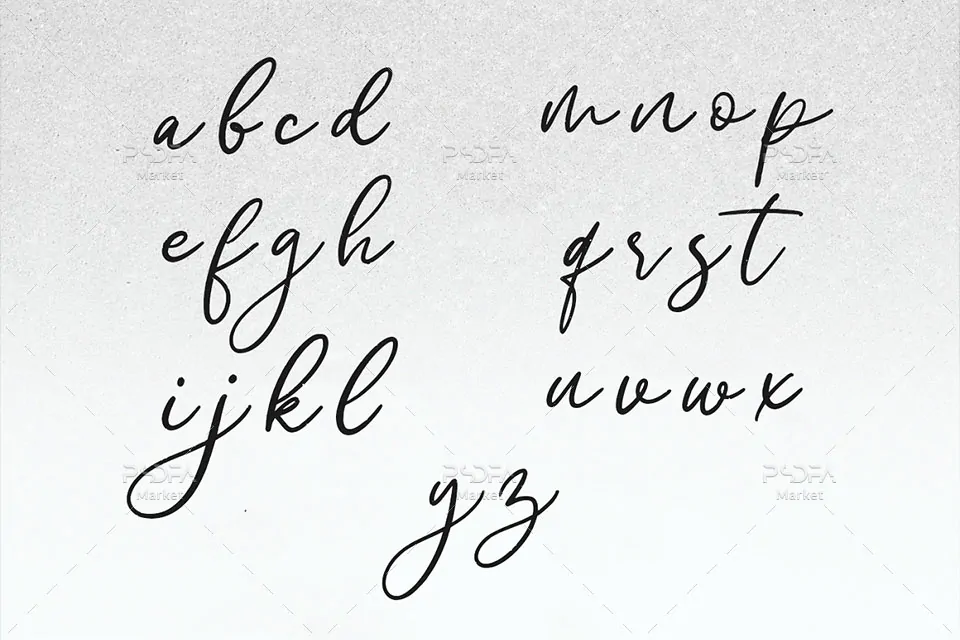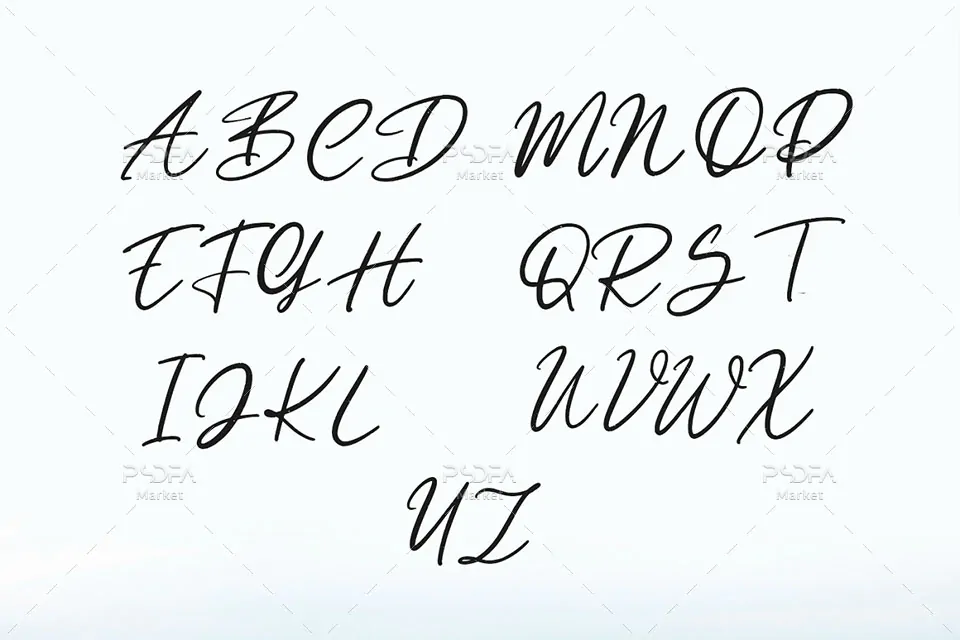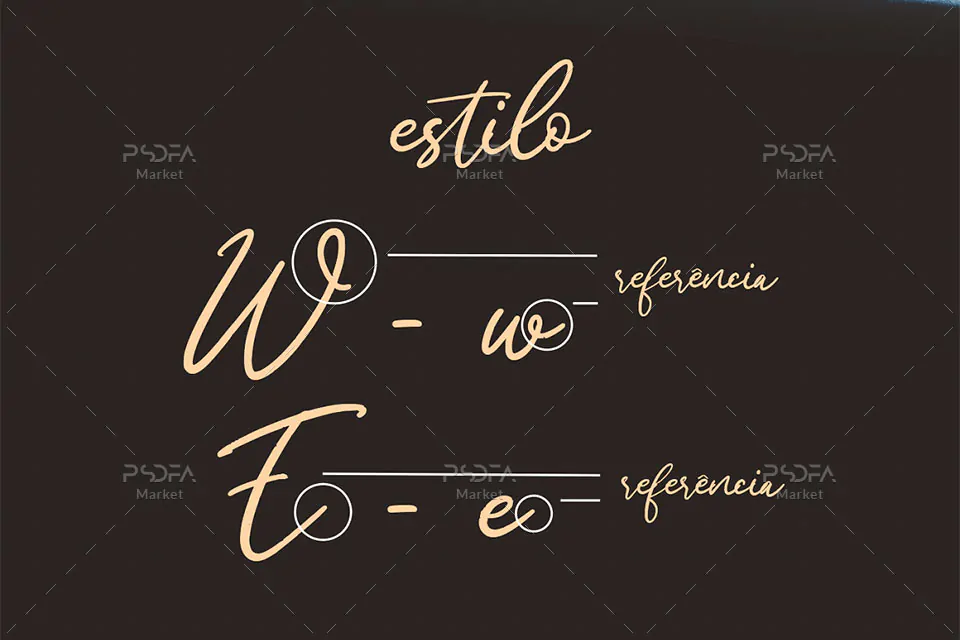
اسکریپت فونت امضایی Welch مناسب برای طراحی و گرافیک
اسکریپت فونت امضایی Welch
اسکریپت فونت امضایی Welch یک قلم زیبا است که به صورت دستنویس طراحی شده است و مناسب جهت استفاده در طرح و پروژههای گرافیکی به خصوص طراحی انواع پوستر میباشد. این فونت در قالب یک فایل TTF بر روی سایت قرار گرفته است که با نصب آن در پوشه فونتهای سیستم خیلی ساده و راحت میتوانید از آن در نرمافزارهای مختلف همچون فتوشاپ، ایلاستریتور، مجموعه نرمافزار آفیس و … استفاده کنید.
فونت Welch در وزن معمولی (Regular) طراحی شده است که شما میتوانید از آن در طراحی انواع کارت تبریک، کارت پستال، کارت ویزیت، طراحی انواع بنر یا پوستر، تراکت، تقویم و دیگر طرحهای گرافیکی استفاده کنید.
- کیفیت بالای قلم